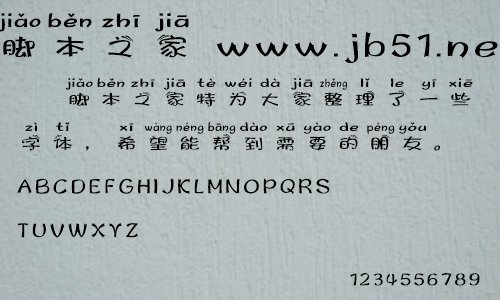
加油你是最胖噠由XFont字庫出品的藝術(shù)字體,字體筆觸較粗細(xì)適中,漢字拼音同步,字如其名,字形有點(diǎn)胖胖的并且短短的,看上去十分的可愛,適合應(yīng)用于藝術(shù)設(shè)計(jì)、平面宣傳設(shè)計(jì)、網(wǎng)頁設(shè)計(jì),書法字帖等領(lǐng)域。有需要的朋友快來本站下載使用吧!